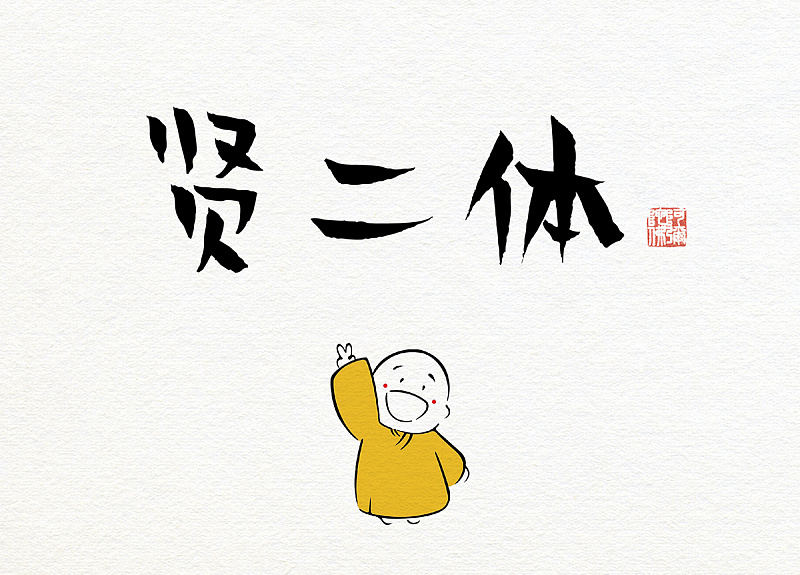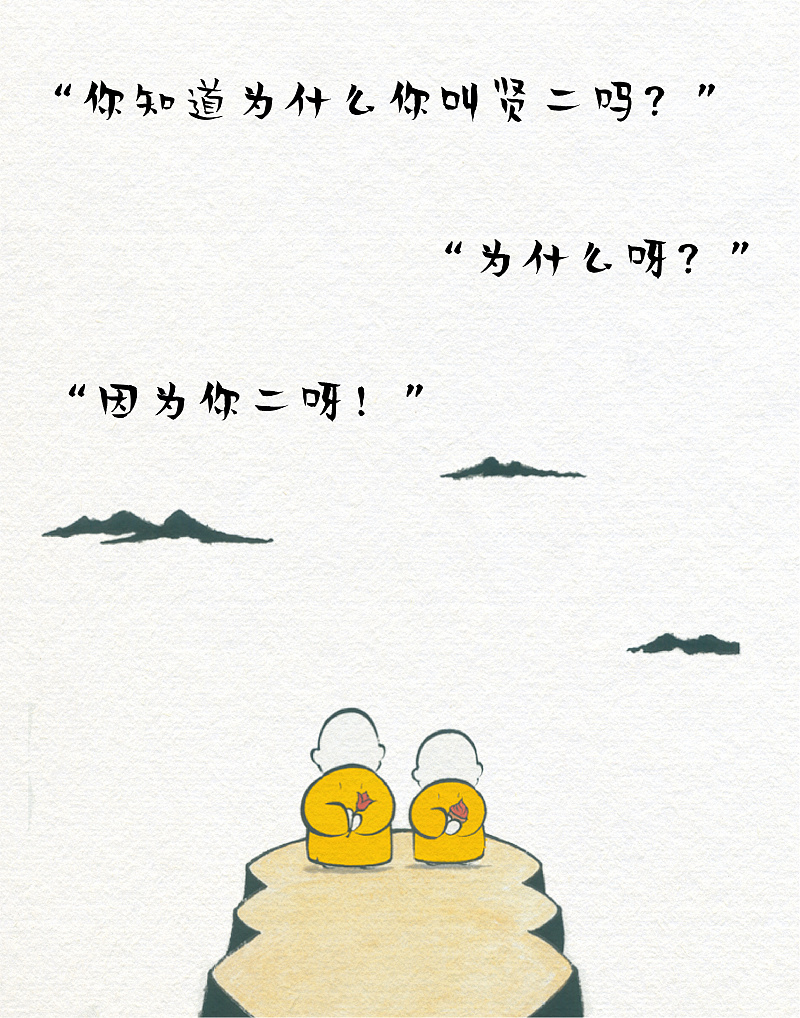
人們常說,字如其人,
橫、豎、撇、捺,
每一筆皆是思緒的演繹,
寫字如修行,
做一套字庫,也是渡己渡人。
北京龍泉寺動漫中心 × 漢儀字庫
賢二體 傾情上線
賢二體是北京龍泉寺動漫中心與漢儀字庫聯合推出的一款商用免費字體。
賢二,
是不二寺的小和尚,
一口氣能吃十個冰激凌。
他很聰明,但是又很懶惰,
總是需要師父點撥。
師父經常會講一些飽含哲理的話語,
幫助我們排解壓力,
告訴我們,
其實,快樂就是這麼簡單。
賢二體的字形偏長,起筆收筆鋒利且粗細對比明顯,筆畫笨拙微帶曲線感。字體組合結構鬆散,重心不穩,達到詼諧幽默,惹人喜愛的效果。
賢二體字形結構和筆畫的特點恰好符合賢二小和尚的性格特點,與龍泉寺學誠法師所傳達出的:“世俗生活裡,人還是二一點比較好”如出一轍。